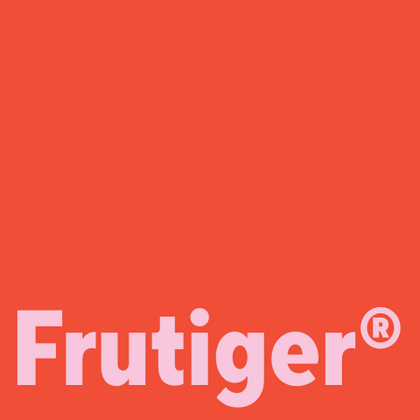
Шрифты похожие на Frutiger
Так же, как и шрифт Frutiger®, аналоги шрифта имеют открытые формы, узнаваемые пропорции строчных букв и плавные переходы толщин. В коллекции TypeType представлены современные альтернативы, которые сохраняют лучшие качества оригинала — дружелюбный характер букв, четкие формы и универсальность применения. Эти шрифтовые решения особенно востребованы в транспортной навигации, медицинских учреждениях и образовательных проектах — везде, где важна мгновенная читаемость.
Если вы устали от «заезженных» шрифтов и ищете гарнитуры, похожие на Frutiger, ознакомьтесь с нашими лучшими альтернативами Frutiger. Это шрифты, которые имеют близкие характеристики, но в то же время обладают новыми уникальными особенностями дизайна. Например, относятся к той же категории шрифтов, подходят для тех же целей и имеют похожие черты, но отличаются в деталях или пропорциях.
Найдите отличную замену Frutiger и попытайтесь имитировать похожее настроение, передать нужное вам ощущение, используя его в своих проектах. Каждый шрифт, представленный на этой странице, является двойником шрифта Frutiger, фактически его полным аналогом.
TT Turns — геометрический гротеск с акцентными круглыми знаками и выразительными нависающими элементами. Это универсальный шрифт, который лаконично выглядит и отлично читается в маленьком размере, при этом в крупных кеглях становится акцидентным и проявляет свой характер на максимум. Он энергичный, сильный и динамичный — особенно отчётливо это проявляется в наклонных начертаниях.
TT Fellows — гуманистический гротеск с механистическими мотивами. Открытые формы, дружелюбно-нейтральный характер тонких весов и ещё более мягкий характер в жирных начертаниях.
TT Chocolates — изящный гуманистический гротеск сo сбалансированными пропорциями, близкими к классическим. Шрифт с приятным дружелюбным характером, который интуитивно воспринимается как что-то знакомое.
TT Wellingtons — это гуманистический гротеск, формы которого отсылают к движению ширококонечного пера. Пластичные линии букв обновлённой гарнитуры, присущие английским гуманистическим шрифтам XX века, выглядят актуально и живо в современных дизайнерских проектах.
TT Commons™ Classic является универсальным гротеском с минимальным контрастом штрихов, закрытой апертурой и геометрическими формами знаков. Дизайн гарнитуры разрабатывался для максимально широкого круга задач, с которыми обязан справляться любой качественный корпоративный шрифт.
TT Hazelnuts — это акцидентная шрифтовая гарнитура без засечек с набором плавных и красивых декоративных элементов. Не смотря на свою геометрическую сущность, в данном шрифте чувствуется след человеческой руки, при желании можно взять перо и поворачивая его нарисовать практически весь шрифт.
TT Corals — это современный гуманистический гротеск, который имеет очень много характерных исторических черт начала 20-го века. Шрифт хорошо подойдет для темы классической литературы или музыки, а также для других самых разнообразных творческих областей человечества.
TT Prosto Sans является шрифтовой гарнитурой на любой жизненный случай. Благодаря современным открытым гротескным формам, вы можете использовать гарнитуру почти для любой задачи.